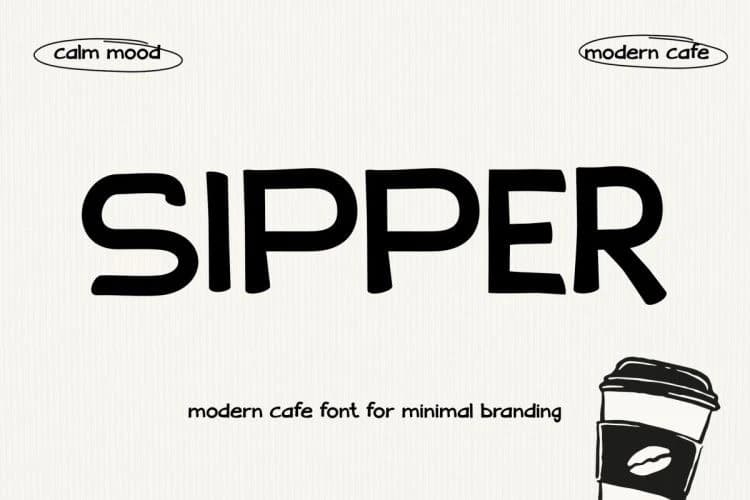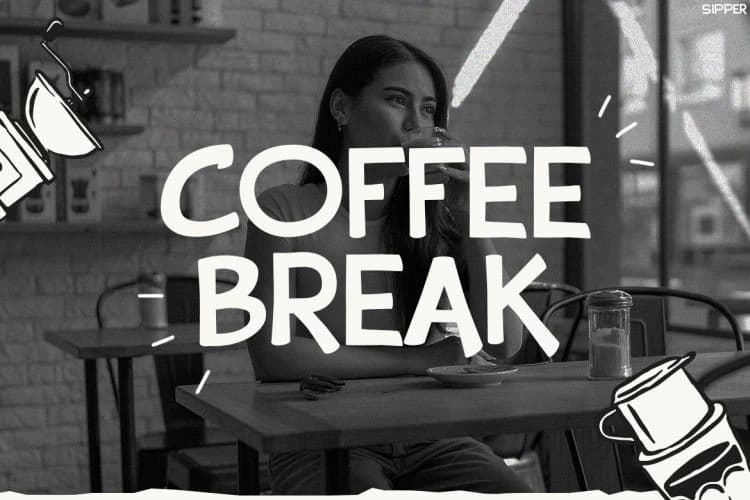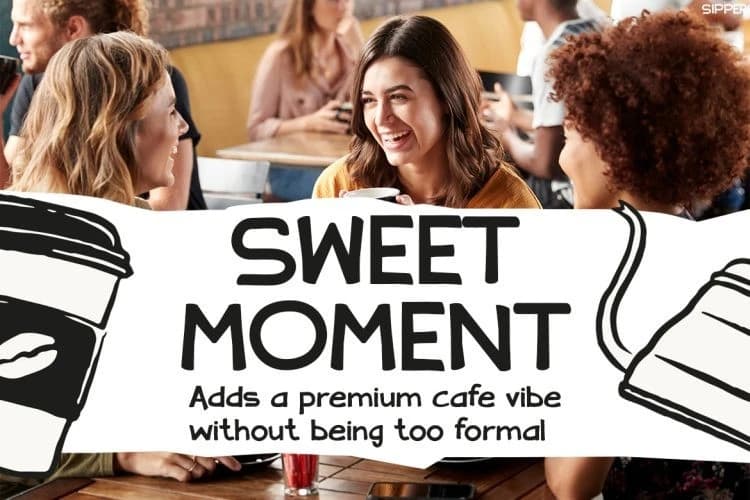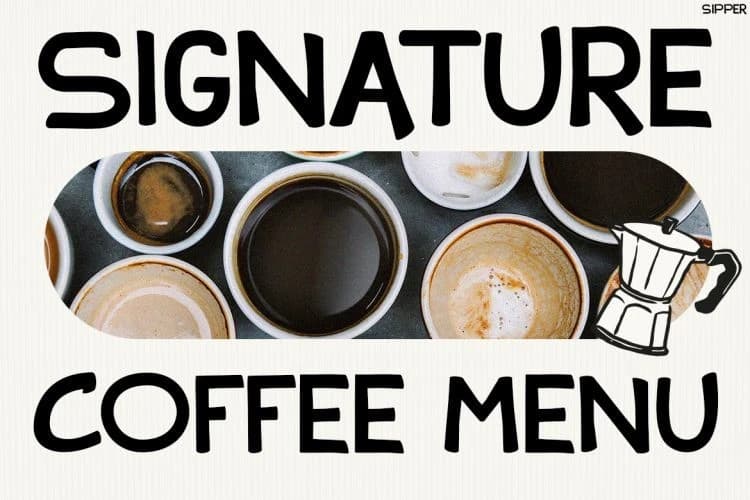
Sipper Playful Font, tasarımlarınıza taze ve samimi bir his katmak için tasarlanmış eğlenceli ve modern bir yazı tipidir. İlk bakışta, kalın yuvarlak hatları ve hafif özgün harf biçimleri sıcak ve samimi bir görünüm yaratır.
Sipper Playful Font, tasarımınıza taze ve samimi bir his katmak için tasarlanmış eğlenceli ve modern bir yazı tipidir. Bir bakışta, kalın yuvarlak hatları ve hafif tuhaf harf biçimleri sıcak ve ulaşılabilir bir görünüm yaratır.